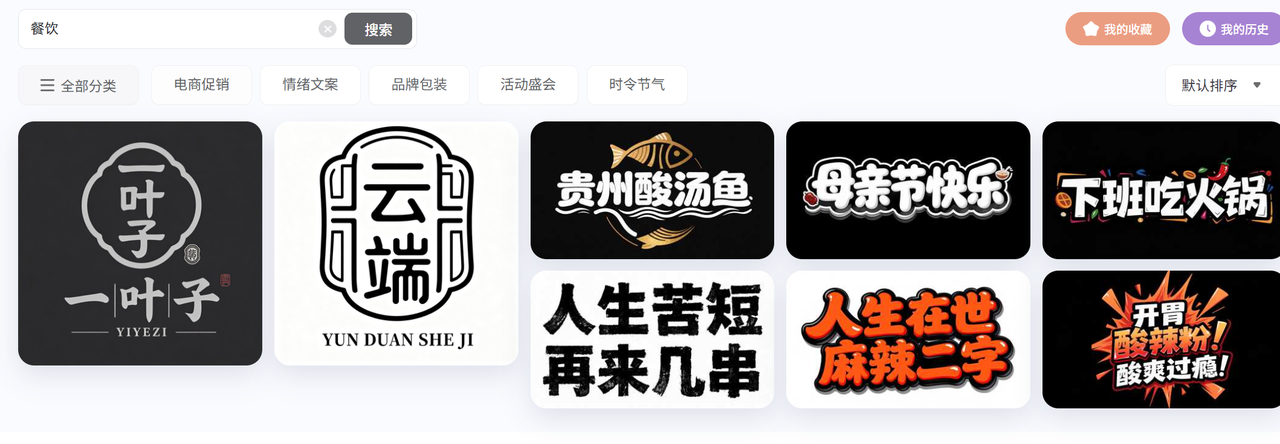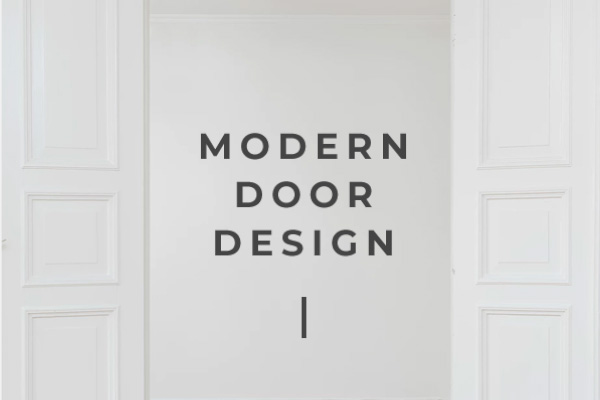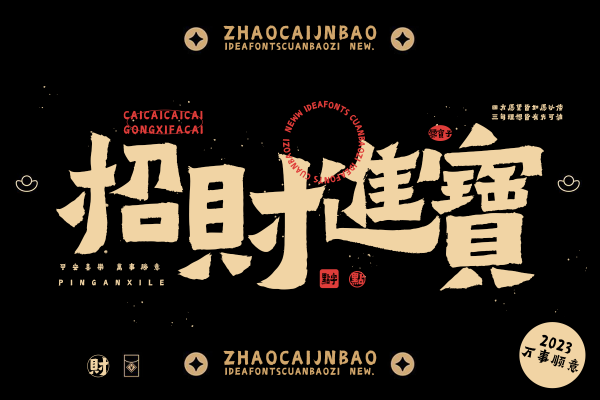
5款适合餐饮的字体推荐,以及 AI 生成餐饮字体的方法
在网络这么发达的时代,餐饮行业的宣传也非常重要,但是招牌不够醒目,菜单看不清,宣传单散发不出吸引力。其实很多人选错字体,我试过不少字体,发现正确选择能让宣传效果翻倍。店名清晰,客人一眼记住,宣传单上文字醒目,流量自然增加。本文给大家推荐一些适合餐饮行业的宣传字体。
Playfair Display
有厚薄对比,高贵有质感。写菜单时像书卷一样优雅。
适合场景:意大利餐厅、西式酒吧、fine dining店的菜单和招牌。顾客在看菜单时,就会觉得店里很有格调。
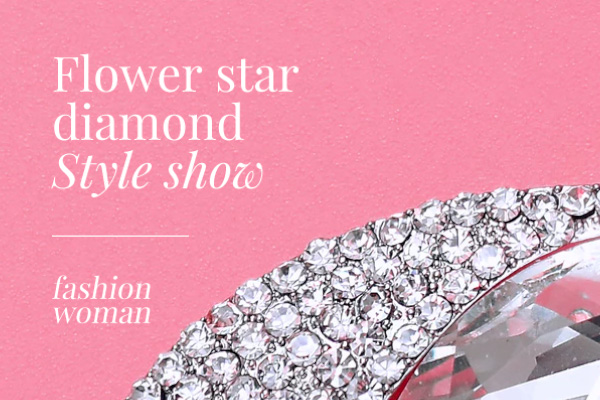
Montserrat
Montserrat 简洁现代,字母形状友好。bold版有冲击力,regular版读起来舒服。适合咖啡馆、甜品店、快餐连锁的门头和海报等场景。宣传时文字醒目,颜色一配就活泼。
点字爨宝子
古朴厚实,有碑文感觉。写起来大气,带山野气息。在商场中看到过很多火锅、烤肉的招聘都很像这个款,适合火锅店、烧烤店的门头和海报。宣传时配图片更像传统美食。
Cabin
Cabin适合小字排版。温暖,圆角设计亲切。适合面包店、轻食店的菜单和包装宣传。文字多时读起来舒服,不累眼。我用这个给甜品店做宣传单,配照片后,
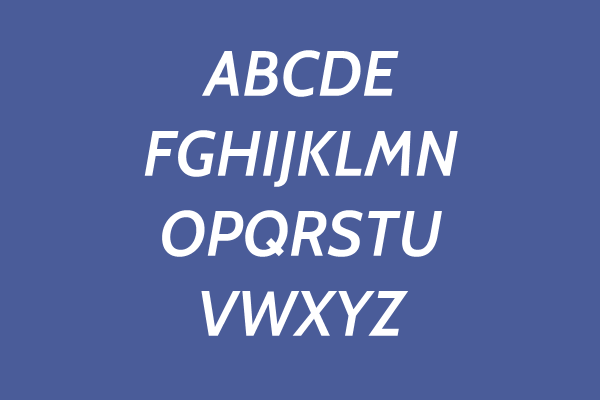
字由油刷
字由油刷手写笔意加现代,笔刷纹理有烟火气。小吃街、街头小吃店的宣传海报和包装。写“油刷”风格的文字更生动。
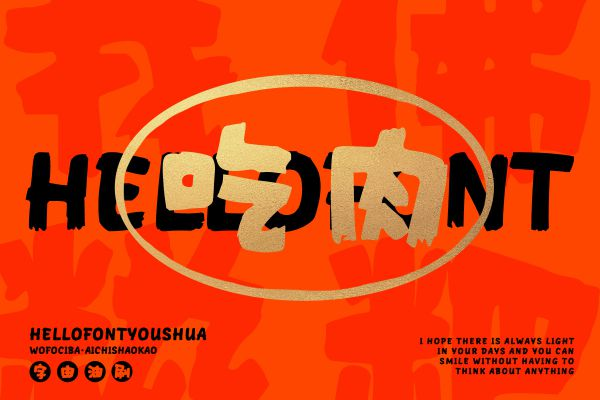
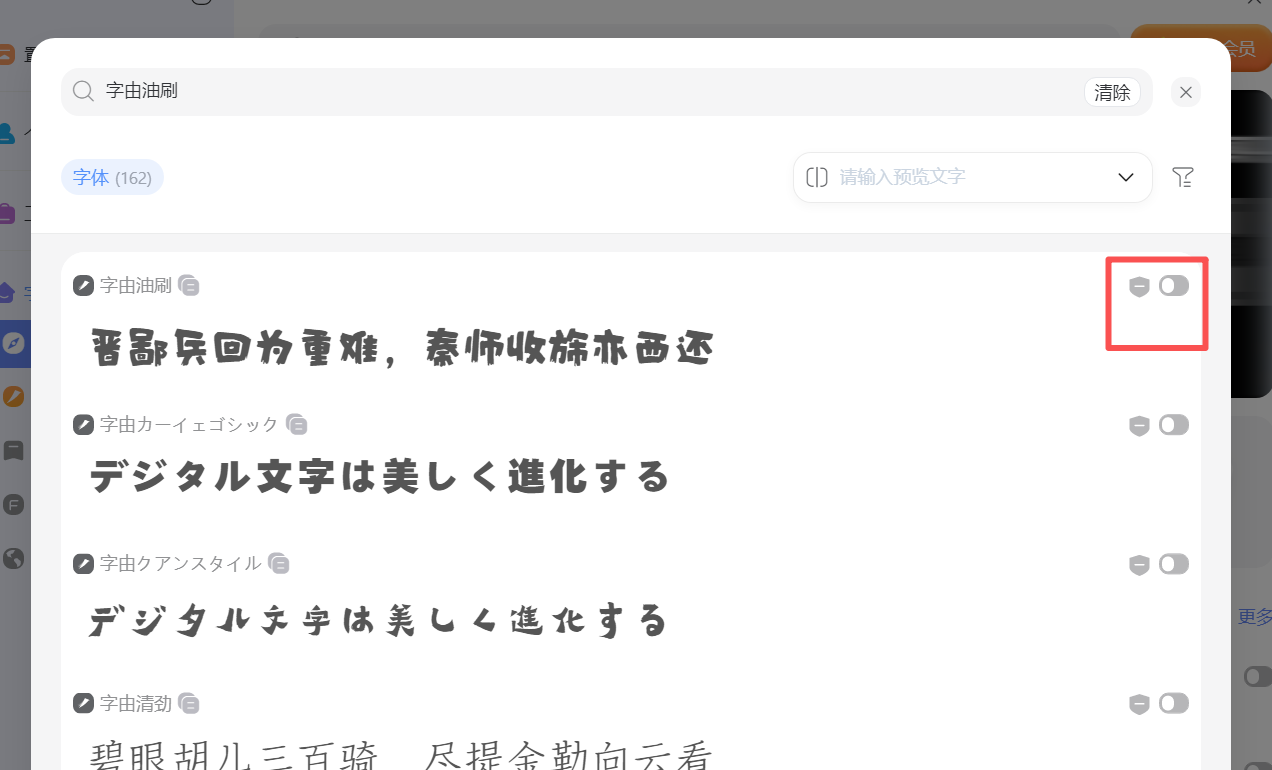
使用 AI 字体生成
字由 AI 字体提供非常丰富的字体模板,选择适合的餐饮模板,就可以一键生成同款字体。
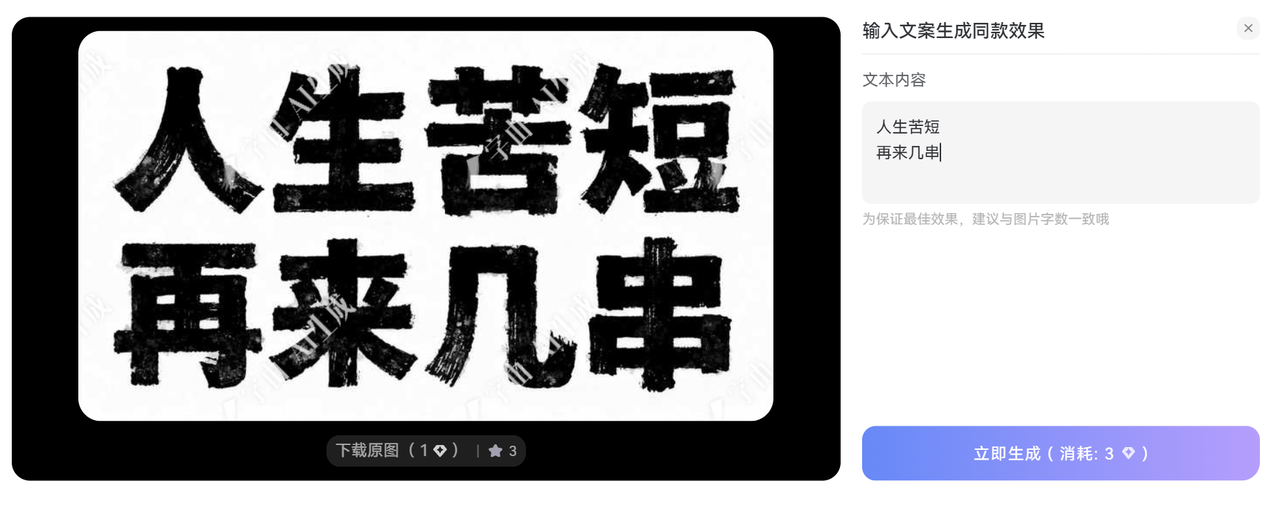
选对字体后,宣传的效果真不一样。招牌看清楚,菜单读不累,宣传单发出去有人点。店面整体看起来专业,客人愿意回来。不同类型餐厅用不同字体,就能匹配自家风格。建议先看字体的预览图,试着用在实际宣传材料上。选对了,就不用再花时间纠结了。
餐厅宣传靠字体传递味道和温暖。正确选择能让客人感受到你店的用心。试试上面推荐的几个以及 AI 生成,找适合自己的字体。